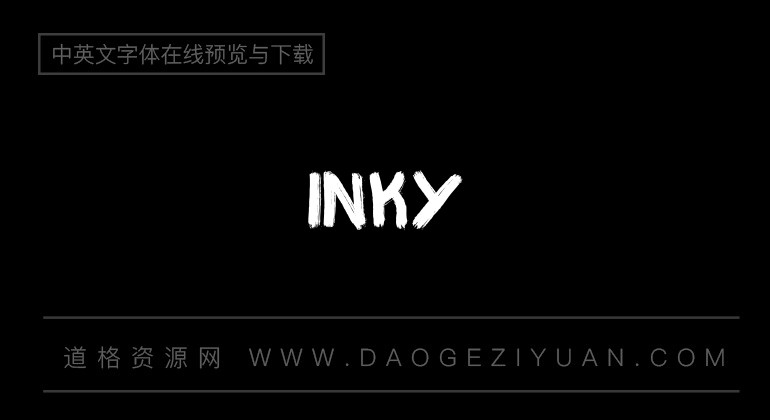
Inky字体是一种新的字体,由FontFont字体公司开发,用于针对手机和平板电脑的设计。它具有独特的视觉效果,使用精致的细节来表达文字。它的设计专注于提高可读性,使文字更加清晰,易于阅读。Inky字体有多种风格,可以满足不同的设计需求,可以用于品牌标识和标题,也可以用于网页和应用程序的文本。内容介绍
Inky是一款非常不错的手写艺术字体,具有很好的视觉感,适合于文化类的宣传设计、商业类品牌的广告和产品包装设计以及个性化文字排版等较多场景。